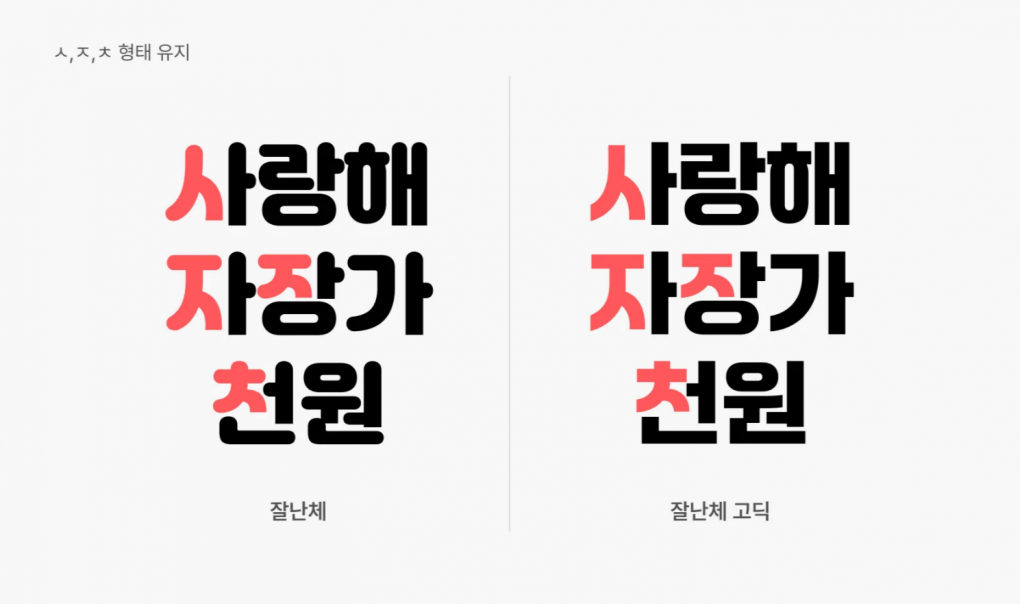
여기어때가 폰트 브랜딩을 꾸준히 하는 이유
5년 만의 잘난체 업그레이드
잘난체의 가족 「잘난체 고딕」의 탄생
기존 「잘난체」는 굵은 두께를 가진 라운드 형태로 귀여운 느낌이었다면, 새로 출시한 「잘난체 고딕」은 끝을 직선으로 처리해 정돈된 느낌을 주도록 했습니다. 그동안 써오던 「잘난체」와는 다른 성격을 가진, 조금 더 다양하게 사용할 수 있는 방향을 고민하게 됐어요. 잘난체의 귀여운 인상을 표현하던 라운드를 덜어내고, 다양한 사용성을 위해 가독성을 강화하는 과정에서 여러 가지 시도를 해 보았죠.
먼저 위의 이미지를 봐 주세요. 「잘난체」와 「잘난체 고딕」이 얼핏 보면 굉장히 유사해 보이죠? 「잘난체 고딕」을 제작하면서 ㅅ, ㅈ, ㅊ과 같은 자음들의 곡선 형태는 유지하려고 했고, 기존 「잘난체」가 꽉 찬 네모꼴에 두께가 어느 정도 있는 제목용 폰트인데, 이 부분도 유지하면서 제작하려고 했기 때문입니다. 이런 눈에 띄는 특징들은 폰트의 인상을 결정짓는 중요한 요소들이기도 하죠.
「잘난체 고딕」 개발 시 기존 「잘난체」와의 연결성을 가져가되, 가독성을 우선순위로 두고 폰트를 만들었는데요, 그러다 보니 기존 「잘난체」와 비교했을 때 자연스럽게 고딕만의 특징이 생기게 된 것 같아요. 획들 사이 공간을 확보하기 위해 이음보에 약간의 곡률을 주었고, 가독성을 높이기 위해 쌍받침 ㄱ의 곡률을 완화하고 받침 ㅍ의 가로줄기와 세로줄기를 연결했습니다. 즉, 특정 자소들에 가독성을 높일 수 있는 장치를 적용한 것이죠!
단순한 이미지가 아니에요. 서비스와 연결된 딩뱃(Dingbat)도 가득!
딩뱃은 쉽게 말해서, 그림문자라고 이해하시면 돼요. 이번 「잘난체 고딕」을 제작할 때, 우리의 서비스와 연결된 딩뱃을 제작하고 싶었어요. 그래서 여기어때의 서비스인 여행, 여가와 관련된 아이콘들을 필요한 곳에 쉽게 사용할 수 있게 추가해 보았습니다.
🖋 딩벳은 총 127개로, 10개의 카테고리 (국내여행, 해외여행, 음식, 숙박, 액티비티, 여행 오브제, 여행 풍경, 결제, 계절/기념일, 감정표현)로 나누어 제작했어요.
사용법은 아주 간단해요! 폰트를 다운로드하고, 해시태그 #과 함께 여행/여가와 관련된 단어들을 타이핑했을 때 자동으로 딩뱃 그래픽으로 변환이 돼요! 위 gif 이미지 보시면, 딩벳이 생성되는 것이 보이시죠?
딩벳은 귀여운 디자인으로 끝나는 것이 아니죠. 폰트와 함께 사용했을 때 너무 작거나 너무 크지 않아야 했고, 연속적으로 딩뱃을 사용했을 때 사이사이 간격도 딩뱃에 비해 너무 넓거나, 좁지 않아야 했습니다. 기나긴 고민의 흔적과, 그 끝에 탄생한 귀여운 딩뱃들은 아티클 전문에서 확인 가능합니다.😊